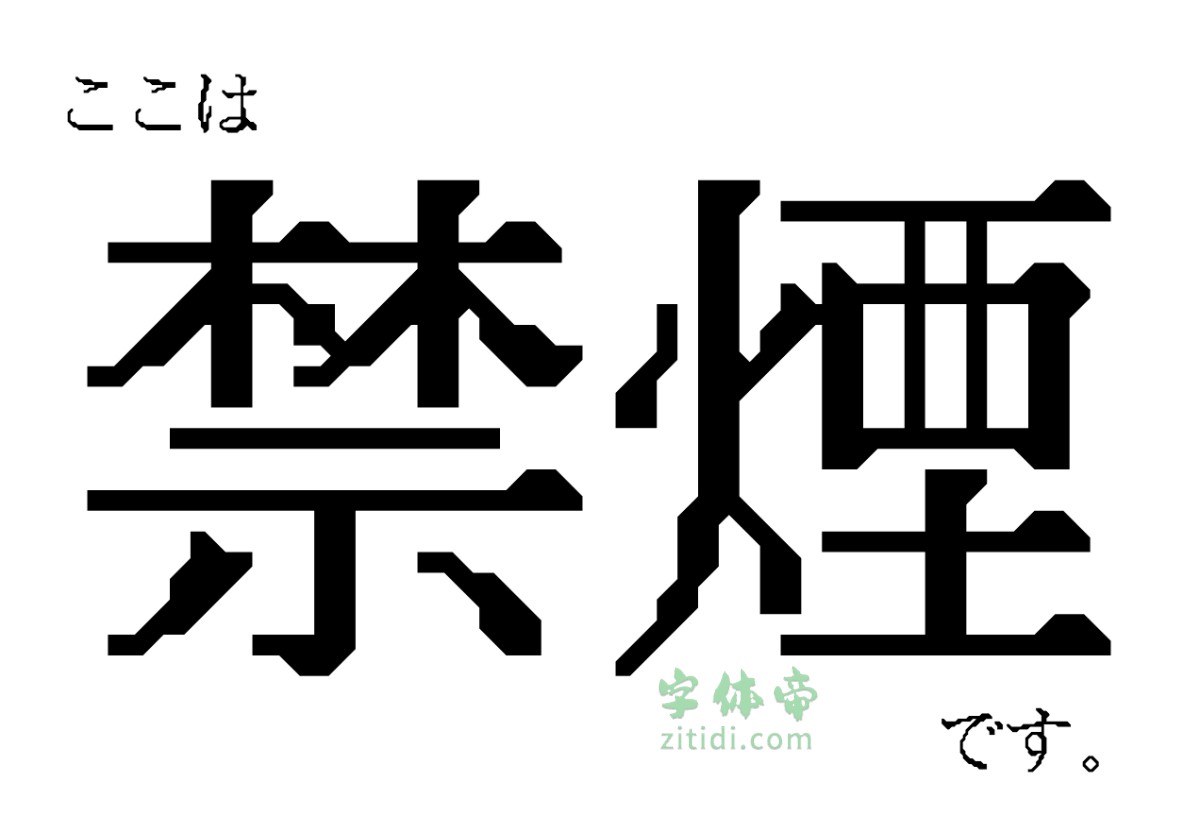
文字处理机明朝(日文名:ワープロ明朝)是一种复制1980年代和1990年代初在文字处理机上使用的位图字体放大过程的字体。
在文字处理机的后期,安装了大纲字体以实现漂亮的放大,但在此之前,位图字体是在打印大字符时放大的。 在此之前,位图字体被用来放大大字符进行印刷。
文字处理机明朝是一种24点的Mincho位图字体,即jiskan24,它经过这种插值处理,形成了一种轮廓字体。